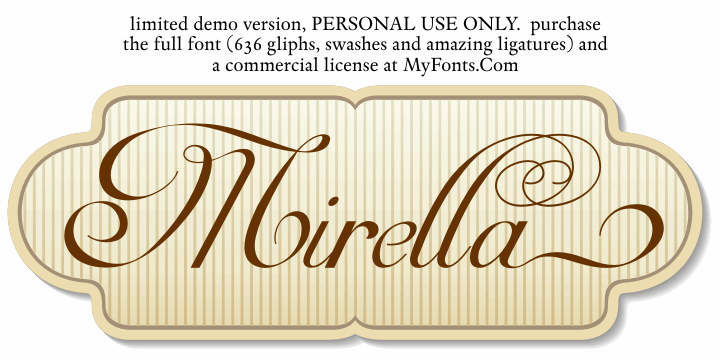
Descubra a beleza única e envolvente do Mirella Script. Inspirada na elegância dos anos 1930, essa fonte script traz uma dose generosa de curvas fluidas e detalhes meticulosamente criados para tornar cada letra um trabalho de arte. Hamilton, o designer habilidoso por trás desta obra-prima, trouxe uma paleta vibrante e sofisticada que vai do vintage retrô até a estética contemporânea. Seja para textos profissionais ou aplicações artísticas, Mirella Script oferece a você uma linguagem visual que impressiona os olhos e se torna uma escolha naturalmente elegante para qualquer projeto. Para adquirir a versão full font completa com 669 glyphs, swashes e maravilhosa ligação de caracteres, visite o site oficial da IntellectaType. Não hesite em explorar essa fonte que revolucionou a maneira como vemos e escrevemos texto.